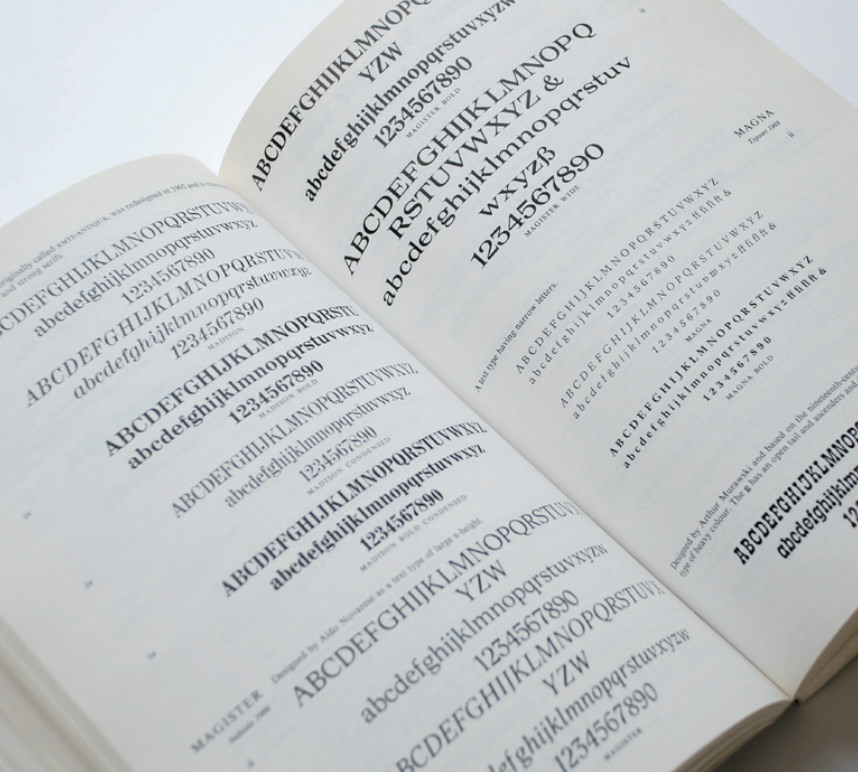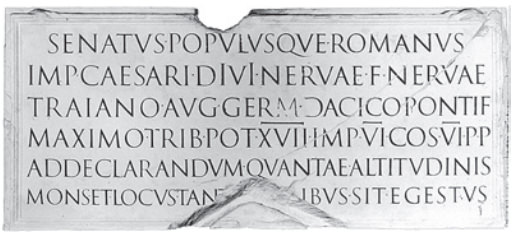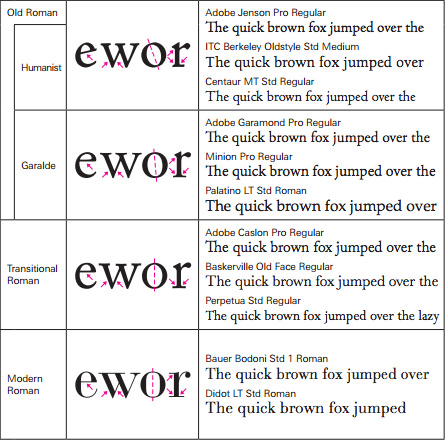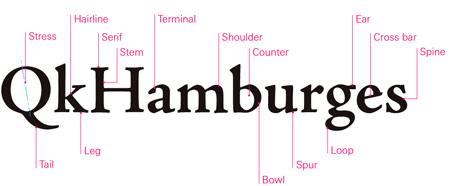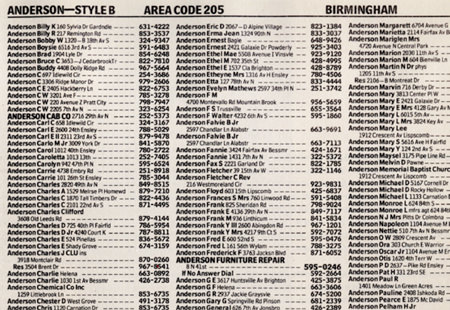
第八回 書 体 を 選 ぶ 1 書 体 を 見 分 け る
これまで、文化的側面から、あるいは技術的な背景から、歴史や事実を検証することで文字を組む方法を見てきましたが、ここからは、文字組みの手順にそって、組版の実際について考察していきたいと思います。まずは、文字を組む際一番最初に考えること。書体選択のお話しです。
書体
見本帳
のこと
書体を選ぶときにかならず必要なものは書体見本帳です。現在(2009年初頭)手に入れることができ、実際に活用できる和文デジタル書体の見本帳は、前回紹介したなかの新しい二冊、『基本日本語活字見本集成 OpenType版』(誠文堂新光社)と『フォントブック[和文基本書体編]』(毎日コミュニケーションズ)でしょう。収録書体数(1650書体)を考えれば前者に軍配が上がりますが、自分が使いやすい方を選べばいいでしょう。
写植時代には、メーカー各社が書体見本帳だけでなく、しっかりした組み見本帳もつくっていたものです。デジタルフォントになって、組みの試行錯誤をデザイナー自身が手軽にできるようになったからかどうか、最近はパンフレット程度のものしかつくらなくなってしまいました。それでもベンダー各々のパンフを集めて自分専用の見本帳をつくってみることをお勧めします。実際私は、編集された見本帳よりメーカーのパンフレットを見ることの方が多いように思います。これも、自分が使いやすいように、ということでしょう。
現在流通しているデジタル書体の見本帳だけではなく、活字や写植書体の古い見本帳も有効です。何より文字を見る目を養うことができます。しかし、古い見本帳は古書としてもなかなか出てきません。現在入手可能なものとして、見本帳ではありませんが、印刷史、書体研究の大著『聚珍録(しゅうちんろく)』(府川充男撰輯、三省堂)を推薦しておきます。もちろん、実際の印刷物を実見することの大切さは言うまでもありません。明治以降の書物であれば、国会図書館や大学図書館で比較的簡単に見ることができます。
欧文書体でも事情は同じですが、書体数も多く、外国語ということもあり、和文書体に比べてしっかりと編集された見本帳を探す必要があります。
また、ほとんどのベンダーがオンラインでフォントを販売していますので、ウェブ上で書体を確認することができます。ただし、印刷文字としてのディティールまで見ることはできませんから、オンスクリーンだけで確認すると、購入してからがっかりすることもしばしばです(体験談)。
評価が高い見本帳として『ENCYCLOPAEDIA OF TYPE FACES』(Blanford)があり、昔からデザイナーが使っている清刷集に『モンセン・スタンダード欧文書体清刷集』(嶋田出版)があります。1990年ごろまで発行をつづけていたモンセンですが、今は古書店でもなかなか手に入らなくなってきました。
それでも古い見本帳は、和文書体より欧文書体の方が見つけやすいと思います。印刷所などで発行された書体見本帳が、資料として大切に扱われてきたことの証なのでしょう。
FontBook(2006年版)
FontShop International
ENCYCLOPAEDIA OF TYPE FACES, Blanford
Jaspert, Berry & Johnson
1953年に刊行されて以来版を重ねている。
写真は、1993年版
欧文書体
の分類
現在、和文のデジタルフォントだけでもおおよそ2000書体が存在しますが、欧文書体はそれと比べものにならないくらい多く、先述の『FONT BOOK』には32000を超える書体が収録されています。しかもこれは市販されている印刷用書体に限った数字です。フリーフォントやエクスクルーシブフォントとよばれる専用書体、またコンピュータディスプレイや携帯電話の表示用書体など、さまざまな用途の文字を加えれば、いったいいくつの書体が存在するのか見当もつきません。そこで、書体を分類して体系的に全体を把握する必要が出てきます。
早い時期に書体数が人の記憶の限界を超えた欧文書体は、書体の体系的な把握もすでに終えており、1960年代には、「VOX-ATypI classification」と呼ばれる分類法が定着しました(Wikipedia; http://en.wikipedia.org/wiki/Garalde#Criticisms)。
VOX-ATypIでは、書体を11種類に分類しており、大きく“時代”と“かたち”のふたつの側面から理解することができます。ここではそれに、“用途”による分類を加えた三つの要素で説明してみたいと思います。
時代に
よる分類
時代別の分類は、古い順から「Old Roman」「Transitional Roman」「Modern Roman」と区分することができます。「Roman」とは、トラヤヌス帝碑文のような、石に彫られた、いわゆる「Roman Capital(ローマ碑文の大文字)」にルーツを持つ、ローマ起源の文字という意味で、日本語では「ローマン体」と総称されています(ラテンアルファベット全体を指す「ローマ字」も、もともとはローマン体の意味だったと推察されます)。広義ではイタリック体に対する正体(垂直に立つ文字)全般を指します。
Old Romanは、グーテンベルクによる活版印刷術発明後のルネサンス期につくられた書体で、印刷術がイタリアに伝来して鋳造されたれたローマン体がこれにあたります。VOX-ATypIでは、イタリアでつくられた最初期(15世紀後半)のものをルネサンス人の人文主義から「Humanist」(地名から「Venetian」とも)、フランスからヨーロッパ各地に拡がっていく後期(16世紀)のものを代表的な書体「Garamond」から「Garalde」と呼んで、2期に分けています。
Transitionalとは“過渡期の”という意味で、Transitional Romanは、Old RomanとModern Romanの過渡期にあたる文字と分類されています。ルネサンス期のイタリアで復活したローマの石碑文字が、フランスからヨーロッパ中に伝搬し、やがてイギリスにたどり着いて、English Romanと呼ばれる書体群を生みます。そのEnglish Roman以降、十八世紀までにできた書体がTransitional Romanです。現在、一番多く流通しているのがこのタイプだといわれています。
最後にModern Roman。“Modern”とは、近世・近代のことを指しますが、活字はルネサンス以降のものですから、すべて近代の所産だということができます。しかし書体の分類では、18世紀後半、産業革命のころに誕生した書風を指して Modern Romanと呼んでいます。まっすぐなステム(縦画)、細い横画などはっきりした特徴を持っており、製紙や印刷技術の進歩がその背景にあると考えられます。DidotとBodoniという代表的な活字鋳造者の名前から「Didone」とも言います。
書体はそれぞれの時代ごとに造形的な特徴があります。簡単に言うと、平筆で書いた手書きの線が、整理され抽象化されていく過程と考えればいいでしょう。数千書体を数える今では、どの時代につくられたかというより、どの時代の文字の特徴を備えているかによって分類しています。また、Modern Roman以降、特にコンピュータで制作されるようになってからの書体を「Contemporary(同時代の)」と呼ぶこともあります。
時代の分け方はおおよそ説明したとおりですが、その名称は国や地域、また考え方によってさまざまです。
トラヤヌス帝の戦勝記念の塔に掲げられた碑文
ローマ、114年ご
時代による分類とその特徴
かたちに
よる分類
かたちといっても、太い細いや、丸い四角いといった形態をみるわけではありません。欧文書体はserif(セリフ)という突起によってかたちを規定してます。
セリフは、石に文字を彫ったときのノミの痕跡、平筆で書いたときの起筆部などを様式化したものと考えられていますが、私は前者をとるのが妥当ではないかと考えています。ローマン体の起源ということもありますが、実際に石に彫っているのをみたときに、セリフの必然性を感じたことをよく覚えています。
そのセリフを持っているのがローマン体。セリフのないのが「Sans serif(サンセリフ)」です。sansとは、仏語で“…のない”という意味です。
サンセリフは19世紀初頭に生まれた文字です。欧文書体の多くは出自(だれがいつどこでつくったか)がわかっているものですが、発生当初のサンセリフ体はそれが明らかではなく、めずらしいボトムアップの(市井の誰かが自発的につくりはじめた)文字ということができます。正統でないことから“グロテスク(奇怪・異様)”と呼ばれていたくらいです。
最初のサンセリフの金属活字は、1816年にウィリアム・キャスロンによってつくられたつくられた「Egyptian」。しかし、実際に普及を見るのは二十世紀に入ってから。「Akzidenz Grotesk」以降のことです。1928年にヤン・チヒョルトがサンセリフ体の使用を基準とした「ノイエ・ティポグラフィ」を提唱し、戦後のスイス派のタイポグラフィを経て、今ではグロテスクでも何でもなく、スタンダードといってもいい存在になりました。
サンセリフはその形態から「Lineal(線状の)」とも呼ばれ、さらに、「Grotesque」「Neo Grotesque」「Geometric」「Humanist」の四つに分けられています。
「Grotesque」と呼ばれる分類は、19世紀のサンセリフ体の特徴を持っており、ストロークにコントラストがあります。1950年代につくられた「Univers」や「Helvetica」が“新しいグロテスク(Neo Grotesque)”と呼ばれるグループで、コントラストは押さえられ、より癖のない、汎用性の高い書体設計が成されています。“幾何学的なもの(Geometric)”は、極端に言えば正円と直線でできていて、20世紀初頭の初期モダニズム期に盛んにつくられました。“人文主義的な書体(Humanist)”はオールドローマン体のような手の痕跡が残るサンセリフです。ルネサンスにおけるヒューマニズムがその呼び名の由来です。
古代ローマやギリシャにもセリフのない文字はありましたが、分類上のサンセリフとは分けて考えたほうがいいでしょう。
もうひとつ、「Slab serif(スラブセリフ)」というグループがあります。 slabは背板など板状のものを表す言葉で、太いセリフを持っている書体を指します。一七九八年のナポレオンのエジプト遠征や、1809年から二六年にかけてシリーズで刊行された書物『Description de l'Égypte』(仏)の影響でおこったといわれるエジプトブームのころ生まれた書風で、エジプト建築の柱の形状と似ているからでしょうか、「Egyptian(エジプシアン)」とも呼ばれています。VOX-ATypIでは、産業革命という時代背景やそのタイプフェイスの力強さから、「Mechanistic(機械的な、力学的な)」と名付けています。
文字の印象についても同じです。タイポグラフィのカンファレンスでヨーロッパの若いデザイナー数人に、「Garamondは日本で人気のある書体ですが、あなたも使うことがありますか?」と聞いたことがあります。答えはいずれも「NO」でした。理由は古くさく見えるから。GaramondはOld Romanに分類される書体です。日本でいえば楷書のようなイメージでしょうか。それを考えてみれば当たり前のことです。Garamondよりモダンなイメージを持つSabonやMinionといった後継書体もありますから、そういう書風がほしいときでも、特別な理由がないかぎり、あえて古典的な風貌のGaramondを使う必要はないわけです。
だからといって、もちろん使ってはいけないということではありません(私はその後もGaramondをよく使っています)。書体選択には根拠が必要だと思うのです。
書体は自由に感覚的に選べばいいというのも一面の真理ですが、その感覚に共通の歴史的、文化的背景があるかどうかを一考すべきでしょう。その背景の違いや個人の感覚の誤差を埋めてくれるものは知識しかないと私は思っています。